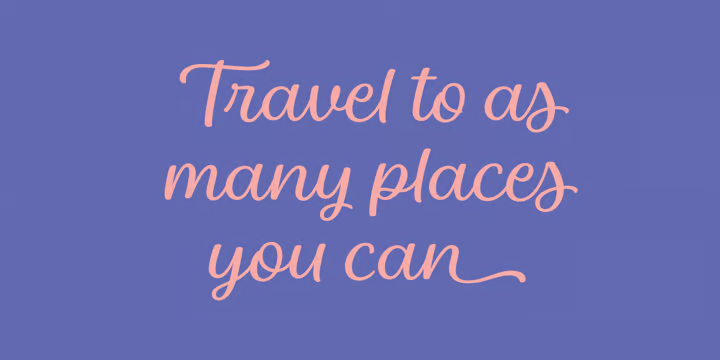
Voyage Typeface
Romantique et sinueux, comme devrait l’être un road-trip, Voyage est très séduisant. Voyage est une police d’affichage, utile pour les titres ou les textes courts à moyens. De l’œil aventureux du « e » minuscule au « h » bouclé, Voyage présente des lignes de cheveux délicates pour un maximum de contrastes. Nous avons conçu 55 ligatures stylistiques, 26 variantes, programmées en type ouvert, l’utilisateur décide quel glyphe alterner. Nous aimons voyager, oublier Paris parfois et embrasser les idées du monde entier. Bon voyage.